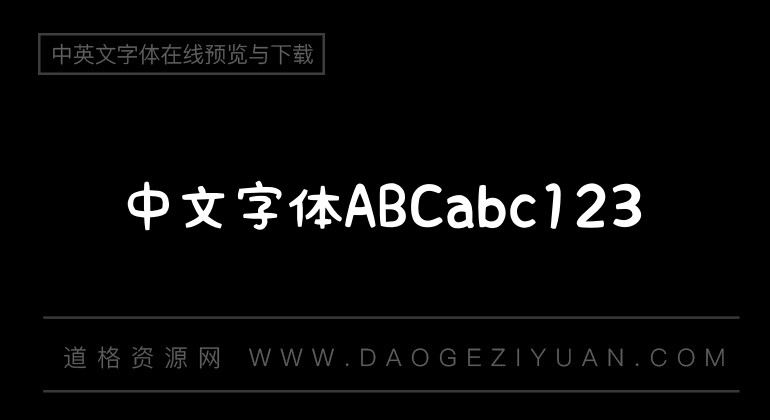
KF手写体
KF手写体是一种中文手写风格的字体,它带有一种独特的个性化和艺术化的气息。这种字体是由设计师Kou Fang创建的,因此得名KF手写体。 KF手写体的特点是其线条柔和、曲线流畅,字形自由、生动,字母间距宽松,整体风格简洁、自然。它适用于多种应用场景,例如宣传海报、文案设计、书籍排版、品牌标志等等。 KF手写体具有良好的可读性和印象力,因此在品牌设计和视觉传达方面特别受欢迎。该字体也非常适用于各种印刷媒体,如广告、海报、手册、包装等。 总之,KF手写体是一种非常流行的中文手写字体,其个性化和自然的风格使其在不同的设计领域得到了广泛的应用。
KF手写体是一款非常不错的手写艺术字体,具有很好的视觉感,适合于文化类的宣传设计、商业类品牌的广告和产品包装设计以及个性化文字排版等较多场景。